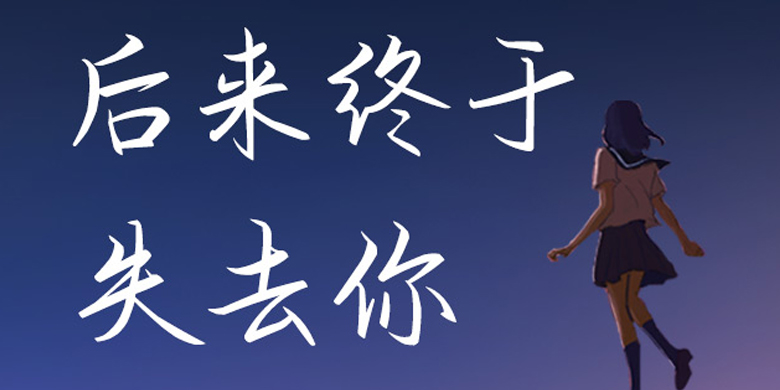
方正手迹-后来终于失去你
字体品牌: 方正手迹 设计师:刘殿儒 字体分类:创意书写 字体属性:精品字 字符集:简繁扩展(GBK) 发布时间: 2020
后来终于失去你这款字体笔触灵动传神,颇具古意,线条沉稳,字形中和圆融,沉静自然。适用于文艺类的书刊、品牌广告和产品包装设计,以及社交网络的个性化用字。